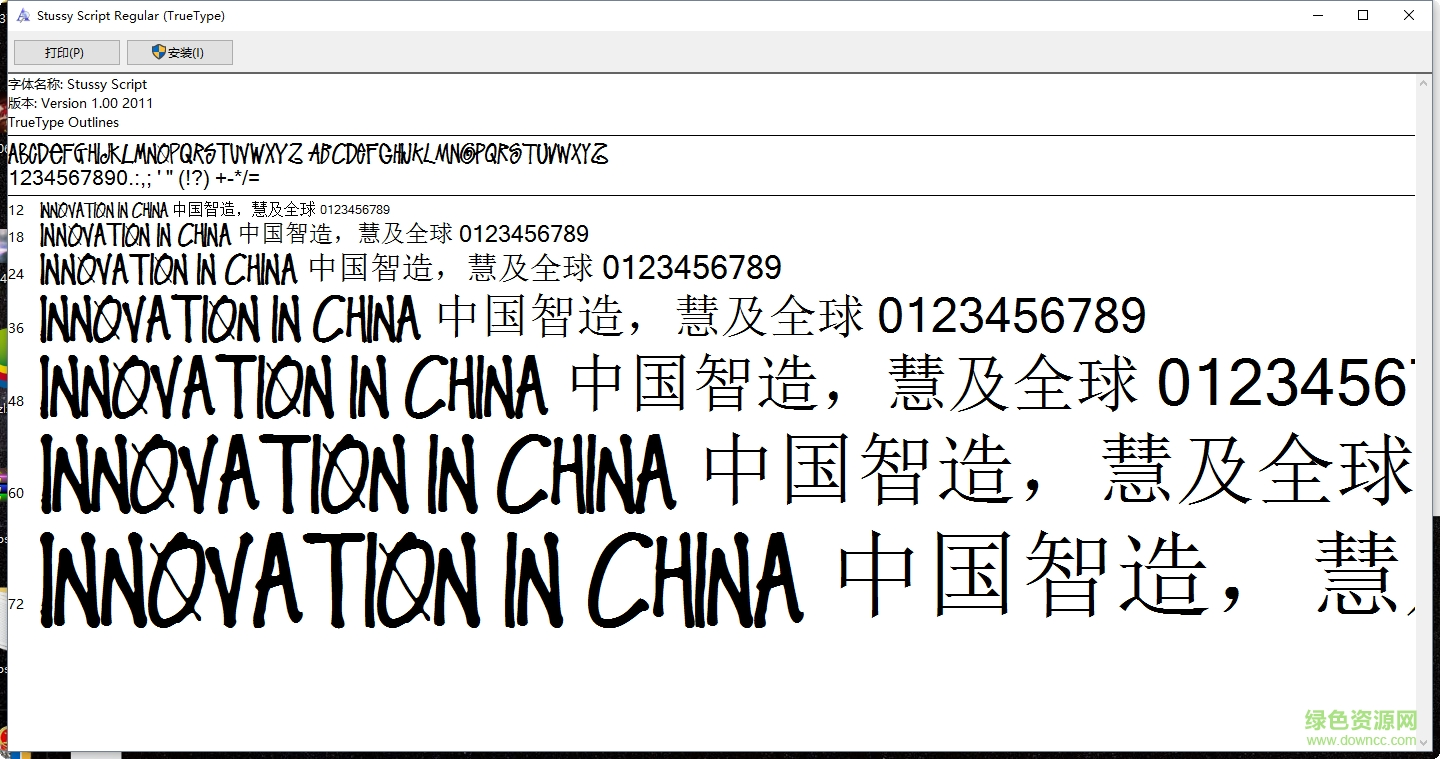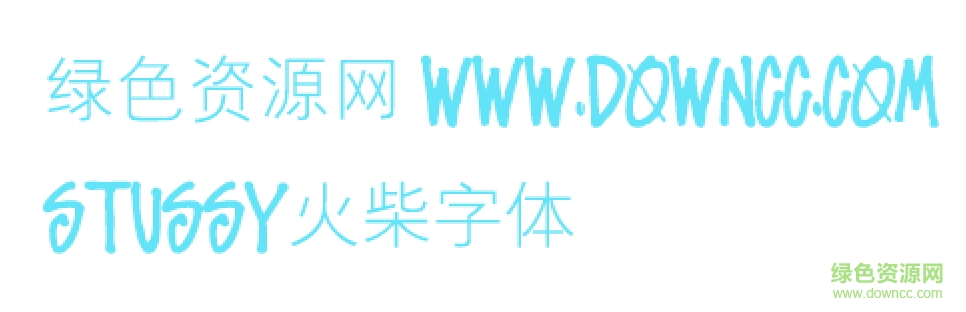
stussy火柴字體
stussy字體即Stussy Script火柴字體。這款字體非常有特色,適用于設(shè)計(jì)海報(bào),廣告制作等方面。歡迎感興趣的用戶來(lái)綠色資源網(wǎng)下載使用。
stussy火柴字體介紹
stussy字體是一款非常實(shí)用的中文字體,該字體線條粗細(xì)適中,中文字體端正大方,英文字形飄逸大方,整體風(fēng)格非常的出色,并且字庫(kù)完整,可用于藝術(shù)設(shè)計(jì)、包裝印刷、簽名設(shè)計(jì)、圖形設(shè)計(jì)等領(lǐng)域